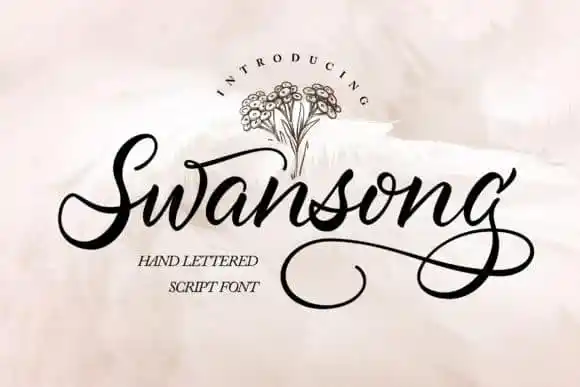
Swansong Calligraphy Font
A Swansong Calligraphy Font é uma elegante fonte feita à mão, perfeita para projetos profissionais que buscam brilho e distinção. Cada letra exibe um toque único e encantador, criado pelo designer Vunira em 99designs. Este script elegante se destaca por suas linhas cuidadosamente trabalhadas, combinando harmoniosamente a sofisticação da calligrafia com as delicadas curvas que lhe dão seu nome: Swansong. Com swashes macias e suaves, essa fonte é uma explosão de beleza para qualquer projeto gráfico ou arte de arte. Ela faz do seu trabalho um verdadeiro destaque, garantindo uma aparência singularmente atraente que vai encantar seus leitores. Experimente a Swansong Calligraphy Font e torne seu próximo projeto ainda mais brilhante e memorável.